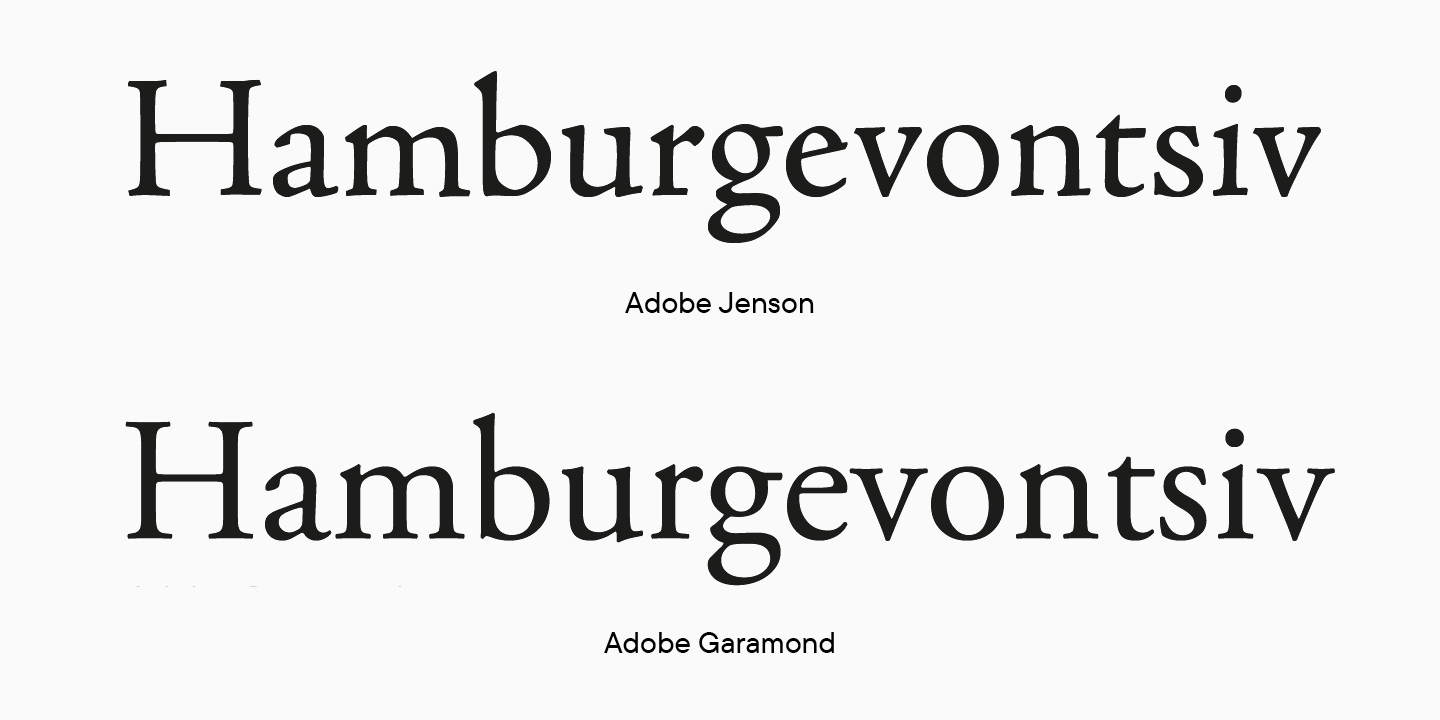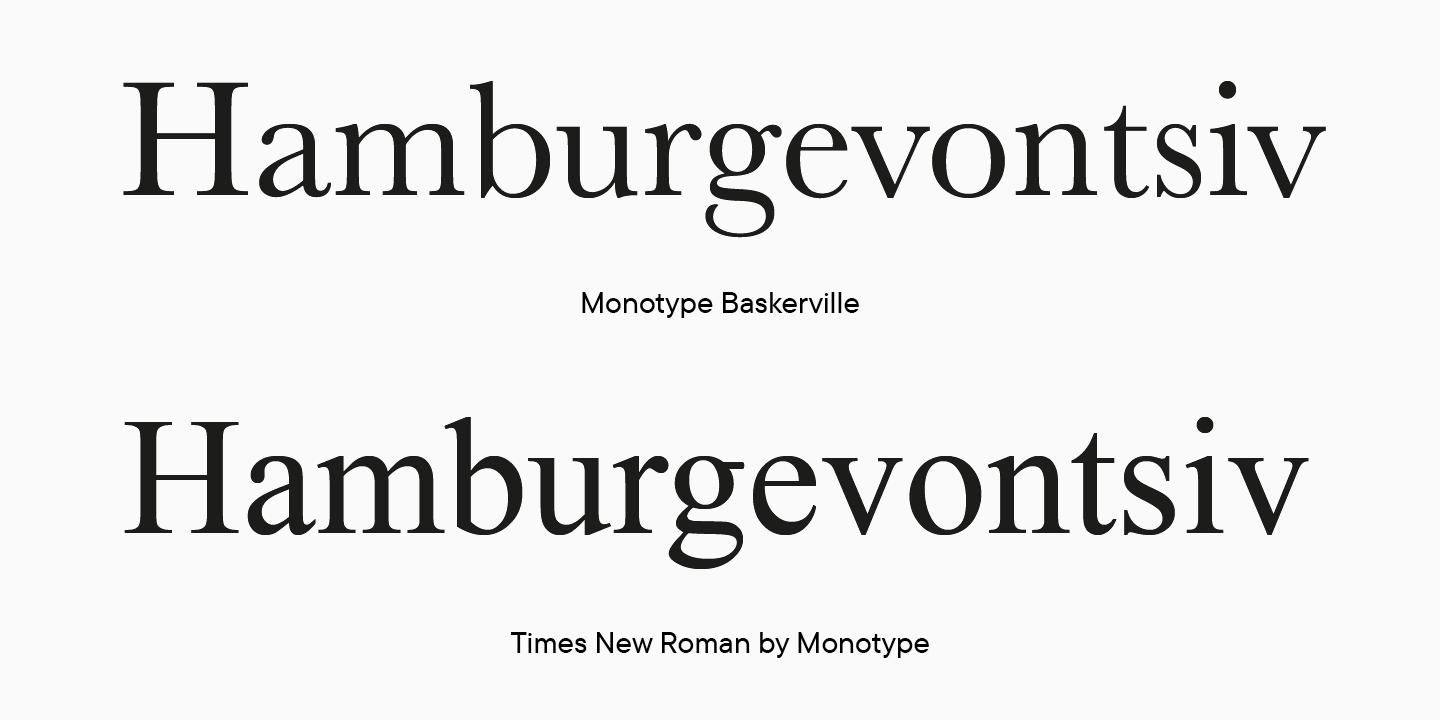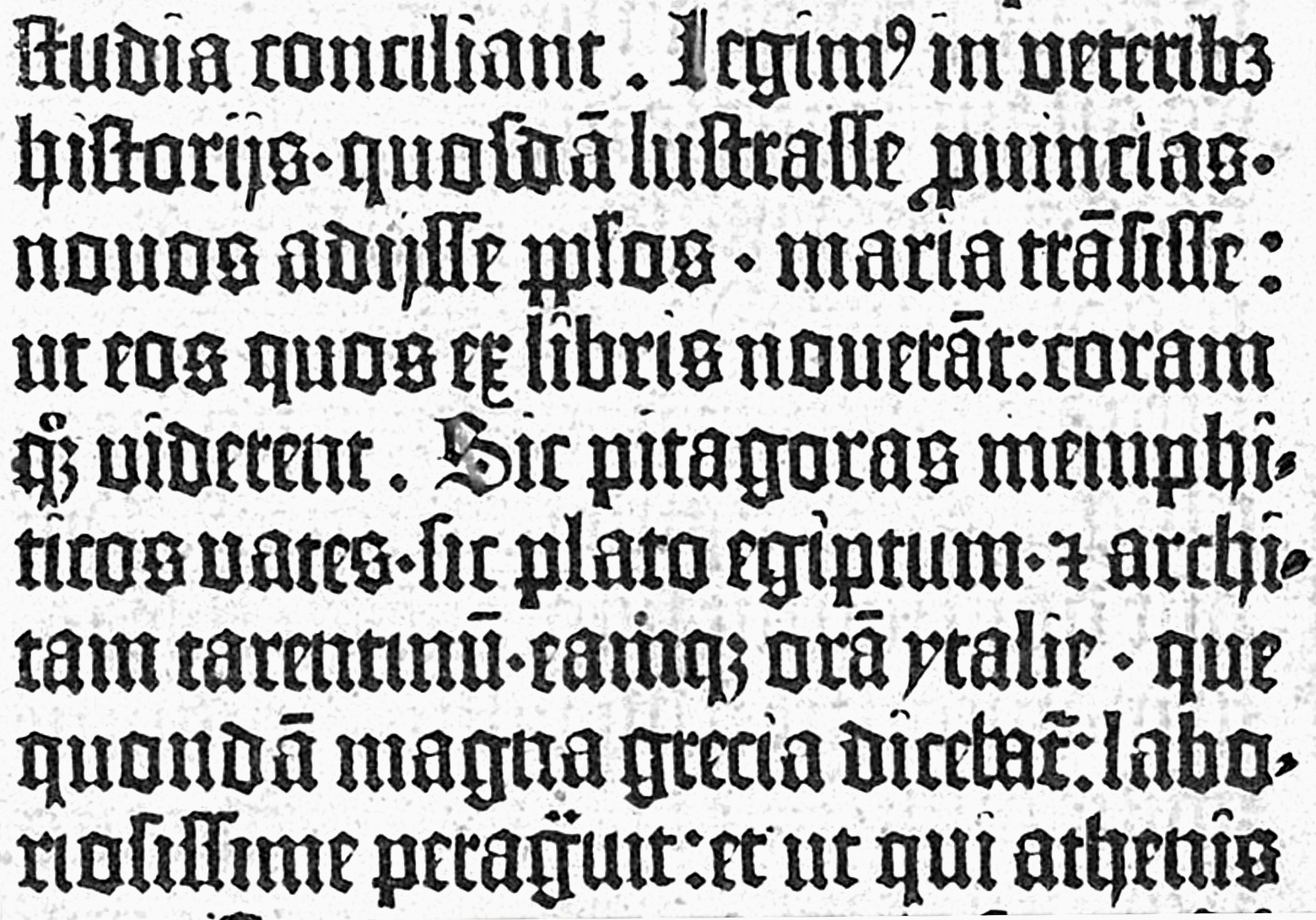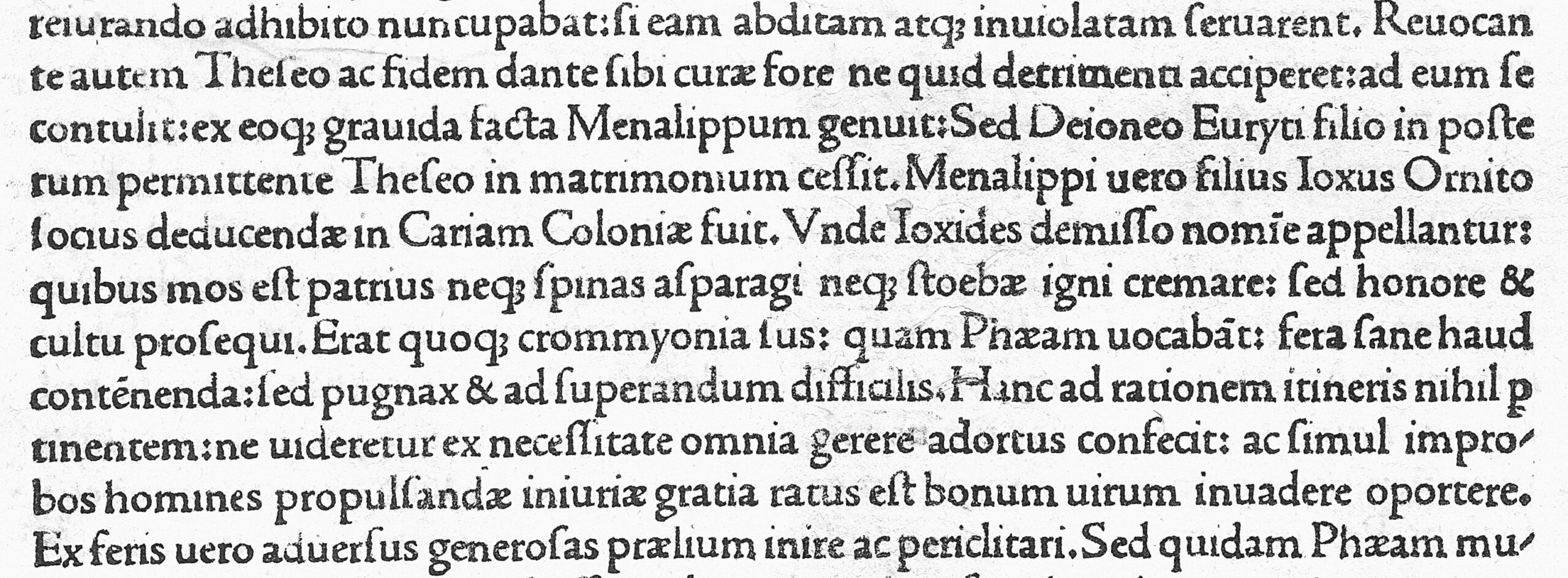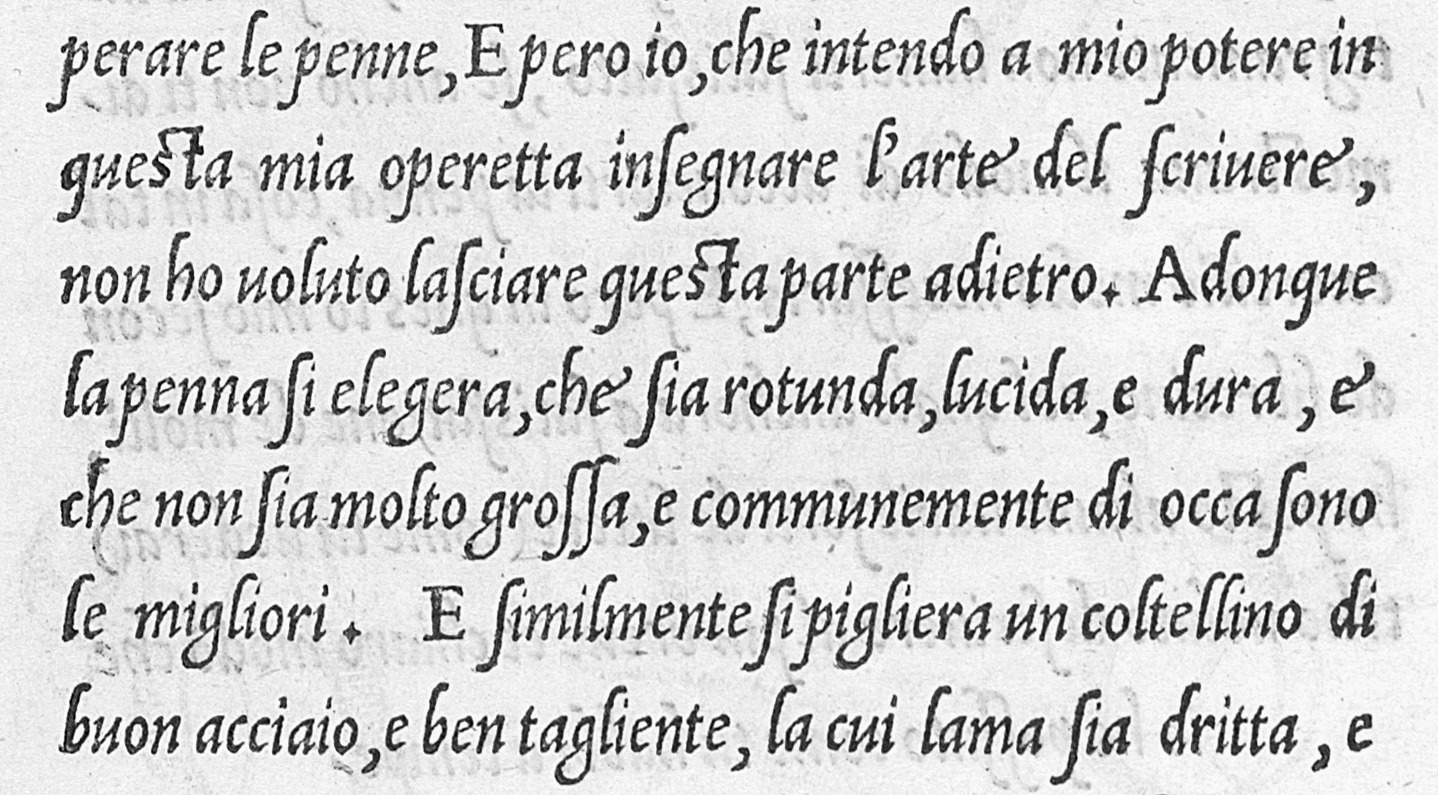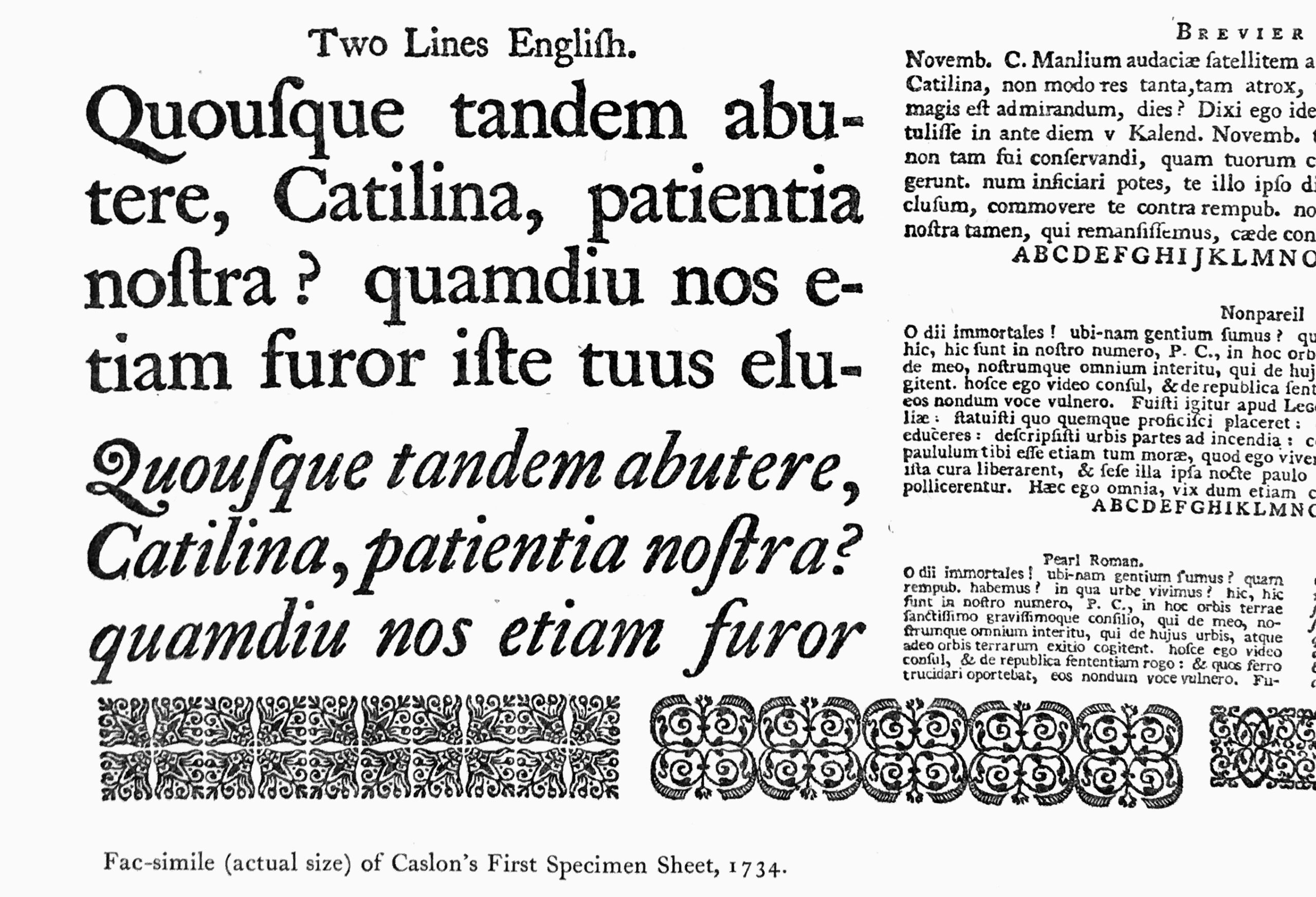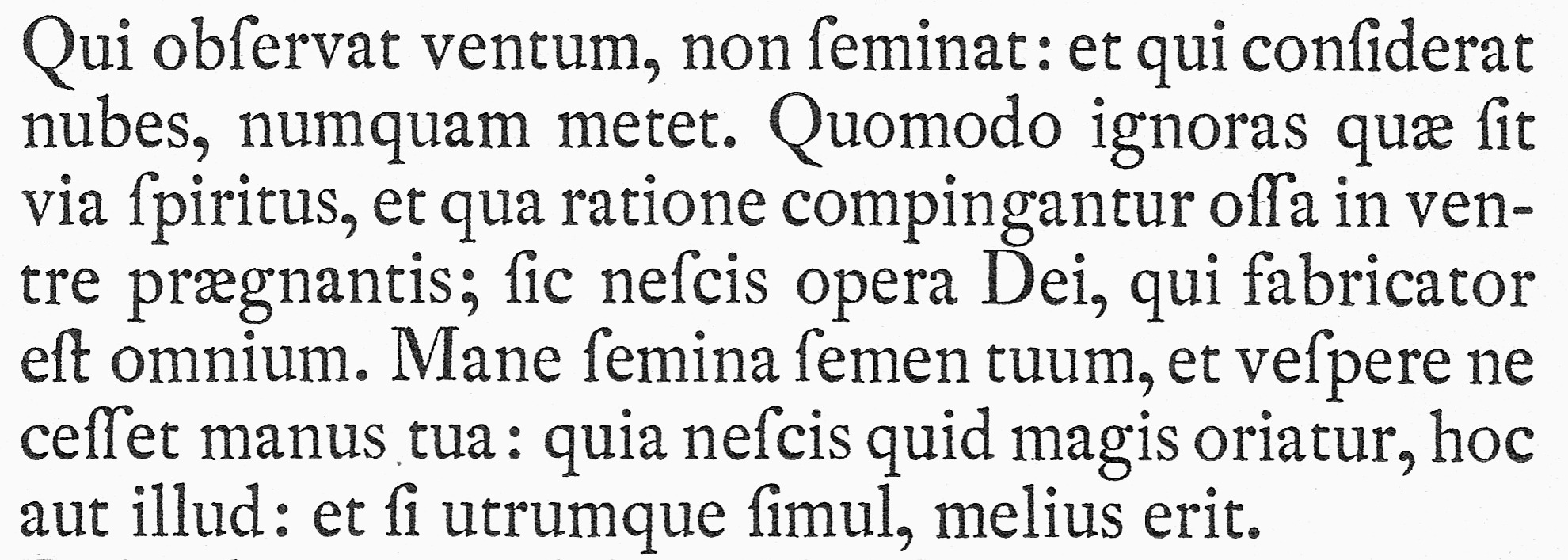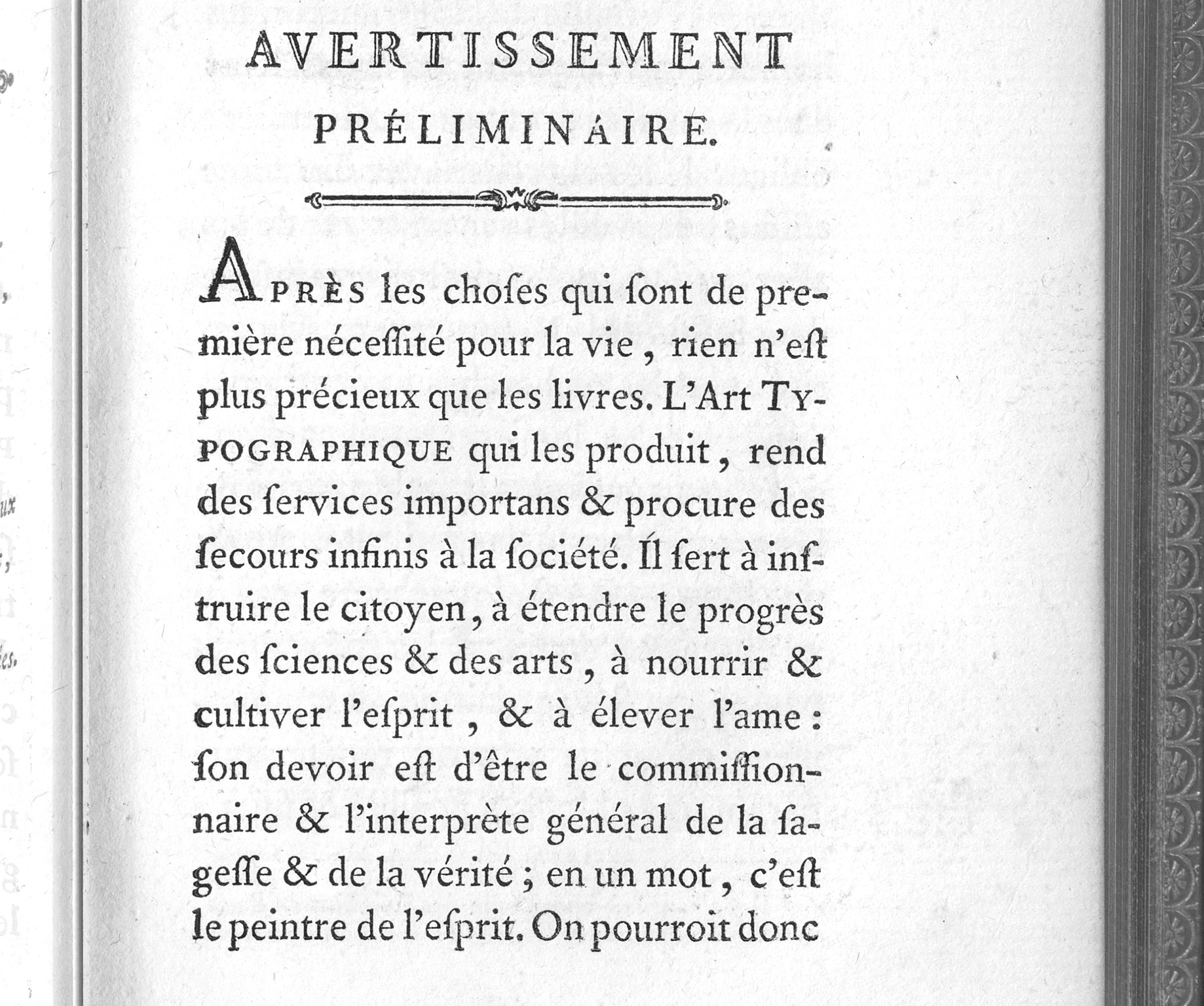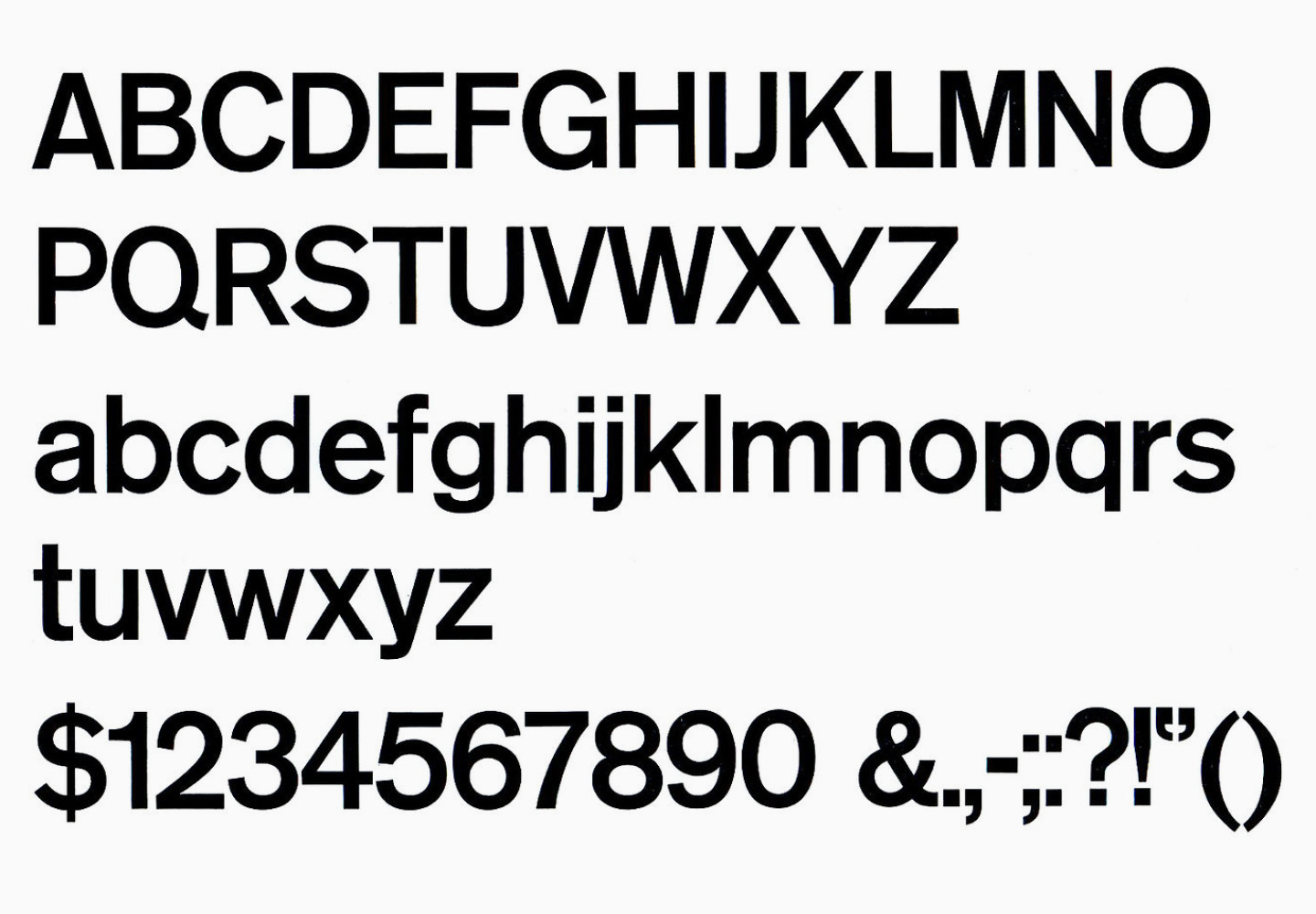
УниверситеТТ: Урок 1. Классификация шрифтов
Эта статья будет необычной. Если вы ещё не слышали, рассказываем: мы запустили новый проект для всех, кто влюблён в шрифты. В рамках этой инициативы мы будем регулярно выпускать материалы о шрифтовом дизайне. Каждая статья из серии раскроет одну полезную тему. А главное — вы сможете не только погрузиться в индустрию, но и познакомитесь с нашей прекрасной командой, ведь делиться опытом будут шрифтовые мастера TypeType.
Даже если вы никогда не занимались шрифтовым дизайном, но очень хотели, присоединяйтесь! Обещаем подавать информацию дозировано, не пугать сложными терминами, а разъяснять их, и сопровождать ваши первые шаги практическими рекомендациями.
Специалистов шрифтовой индустрии мы тоже приглашаем присоединиться, ведь обмениваться опытом и погружаться в процессы коллег по цеху полезно. Это помогает посмотреть на привычные вещи с новой стороны, а иногда даже поймать вдохновение для новых проектов!
Тема этой статьи — виды шрифтов. В эфире — Юлия Гонина, арт-директор TypeType. Шрифты, которые она курировала, стабильно попадают в шорт-листы и занимают призовые места на конкурсах (Granshan, European Design Awards, «Современная кириллица», «Фестиваль среда» и других).
Юля также выступает автором гарнитур студии (TT Livret, TT Fellows, TT Autonomous и другие). Вы могли слышать и видеть её в качестве приглашённого спикера на TDC, Mail Design Conf, «Дизайн выходных», и среди членов жюри на выпуске шрифтовой школы Bold Italic.
Классификация шрифтов
На данный момент нет ни одной чёткой классификации шрифтов, которая позволит с уверенностью категоризировать любой нарисованный шрифт. Всегда найдутся те, что будут находиться на стыке нескольких групп.
Тем не менее, источники с подробной классификацией шрифтов можно найти и в книгах, и в веб-пространстве. Остановимся на некоторых из них.
Типы шрифтов
Самая распространенная классификация была сделана Максимилианом Воксом (Maximilien Vox) в 1954 году, а в 1962 году её взяла на вооружение международная ассоциация типографов (ATypI). Со временем она дополнялась и перерабатывалась разными организациями и теоретиками, поэтому сейчас можно найти много её интерпретаций. Стоит отметить, что с момента появления вышеупомянутой классификации прошло больше половины века. За это время менялась мода, появлялись новые шрифтовые стили и направления.
Maximilien Vox, «Un projet français de nomenclature des caractères typographiques: La classification ‘VOX'», Caractère: revue mensuelle des industries graphiques, Paris, Compagnie française d’éditions, 1954, year 5, 7, p. 87.
Хочу поделиться полезными источниками, благодаря которым можно самостоятельно изучить вопрос классификаций и составить собственную картину шрифтового мира.
• В книге Роберта Брингхерста (Robert Bringhurst) «Основы стиля в типографике» вас ждёт подробный хронологический рассказ об эволюции шрифтовых стилей.
• Книга Letter Fountain от Taschen представит осовремененную и компактную классификацию шрифтов с отсылкой к Максимилиану Воксу.
• На сайте designhistory.org вы можете изучить краткий обзор различных классификаций по их авторам.
В этой статье я не буду заострять внимание на разнообразии классификаций, а постараюсь понятно и просто рассказать про базовые группы шрифтов. Этих знаний будет достаточно, чтобы получить первоначальное понимание того, какими вообще бывают шрифты, и на эту основу вы сможете наслаивать более сложные классификации в будущем.
Начнём с вопроса, который сразу возникает у многих новичков: «А для чего вообще нужны классификации? Разве нельзя работать без этих знаний?». Конечно, можно. Современные шрифты часто создаются без привязки к конкретной исторической группе, и в этом нет ничего плохого. Шрифтовые дизайнеры больше полагаются на собственную насмотренность, чувство эстетики и актуальные вкусы. Однако сказанное выше относится скорее к опытным специалистам, а новичкам будет полезно иметь представление хотя бы о базовой структуре шрифтов, чтобы не потеряться в их разнообразии.
Итак, начнём с самых простых вопросов: какими бывают шрифты и в чём разница между ними? Представьте скелет буквы, который показывает только её конструкцию. Чтобы получить символ с толщиной и опознавательными знаками, на скелет нужно нарастить толщину. Сделать это можно разными способами.
Иллюстрация скелета и разных категорий шрифтов
Можно равномерно нарастить жирность на всём протяжении скелета и получить гротеск. Если добавить контраст в толщинах, чтобы появились толстые и тонкие штрихи, будто мы писали букву пером, получится ленточная антиква. К ленточной антикве можно добавить засечки на концах штрихов и получить антикву. Либо вернуться к гротеску и добавить букве засечки, которые будут подходить по ширине к штрихам, и создать слаб.